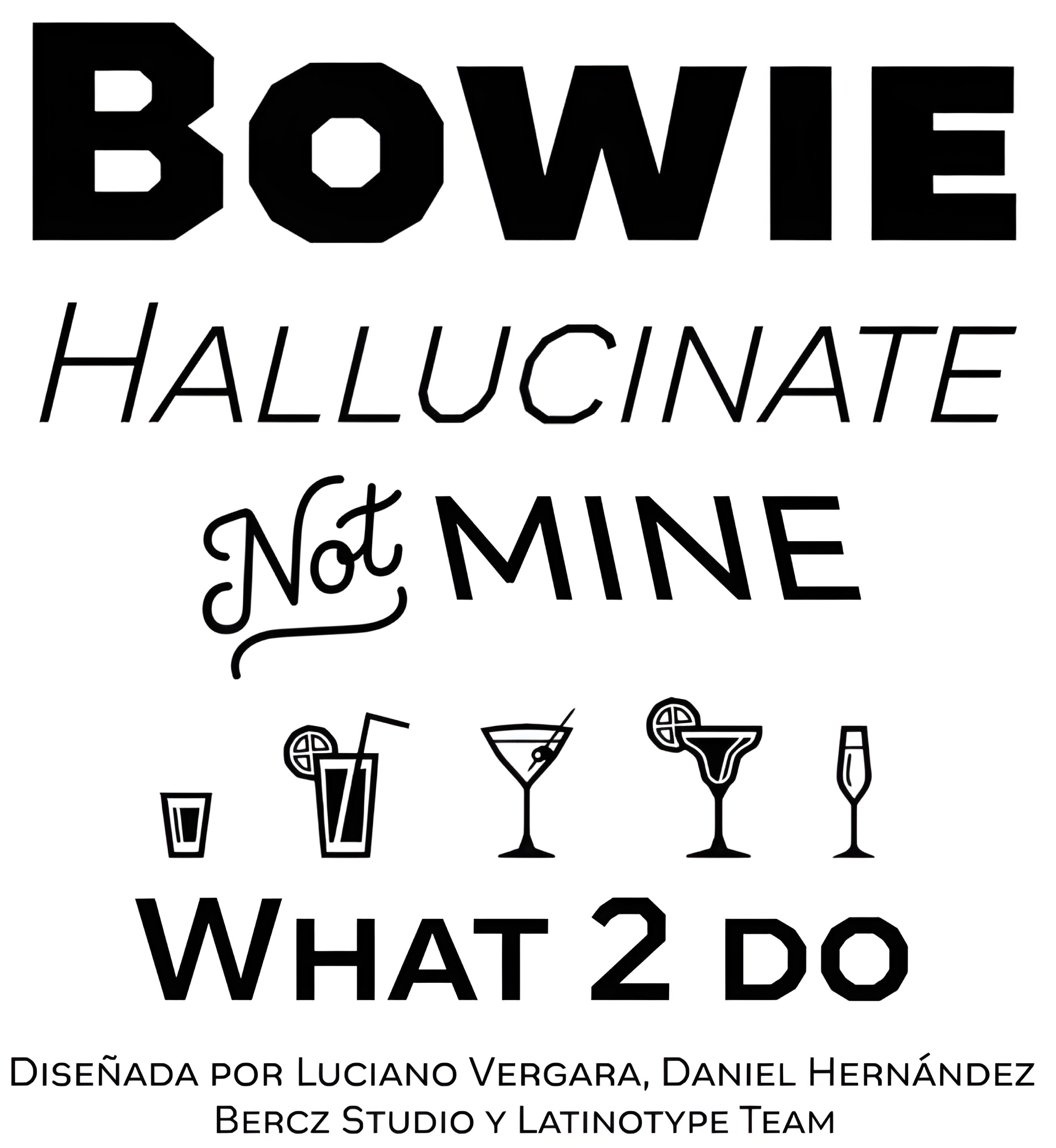
| Créditos | Luciano Vergara, Daniel Hernández, Bercz Studio, Latinotype Team |
| Descripción | El nombre de este tipo de letra procede del apellido de James (Jim) Bowie, pionero estadounidense e inventor del famoso cuchillo Bowie. Esto es exactamente lo que inspiró a la estrella inglesa del rock David Jones a cambiar su nombre artístico por el de David Bowie. Bowie es el nuevo tipo de letra de Bercz y Latinotype Team. Se trata de un sistema tipográfico que refleja una fuerte personalidad, un aire urbano y un estilo desprejuiciado. Bowie es ideal para proyectos editoriales, marcas y envases. Esta familia tipográfica se compone de tres secciones: un grupo de fuentes en mayúsculas de formas afiladas (versalitas y todo mayúsculas) en 5 pesos, cada uno de ellos con su correspondiente cursiva oblicua regular/posterior, que ofrece a los usuarios 15 estilos diferentes para múltiples combinaciones; un conjunto de palabras clave escritas y conjuntos eclécticos de dingbats y banderas que comunican el pensamiento y la sensación de cielo azul del proyecto. Bowie, un proyecto de colaboración entre Bercz y Latinotype Team, fue desarrollado por Leonidas Loyola, Valentina Vega, Rodrigo Fuenzalida, César Araya y Bruno Jara, bajo la supervisión de Dany Berczeller, Daniel Hernández y Luciano Vergara. Bowie consta de 5 pesos, que van de Thin aBlack, y viene con un conjunto de 439 caracteres compatible con 206 idiomas. |
| Clasificación | Títulos, Dingbats |
| Familia(s) | Bowie |
| Estudio | Latinotype |